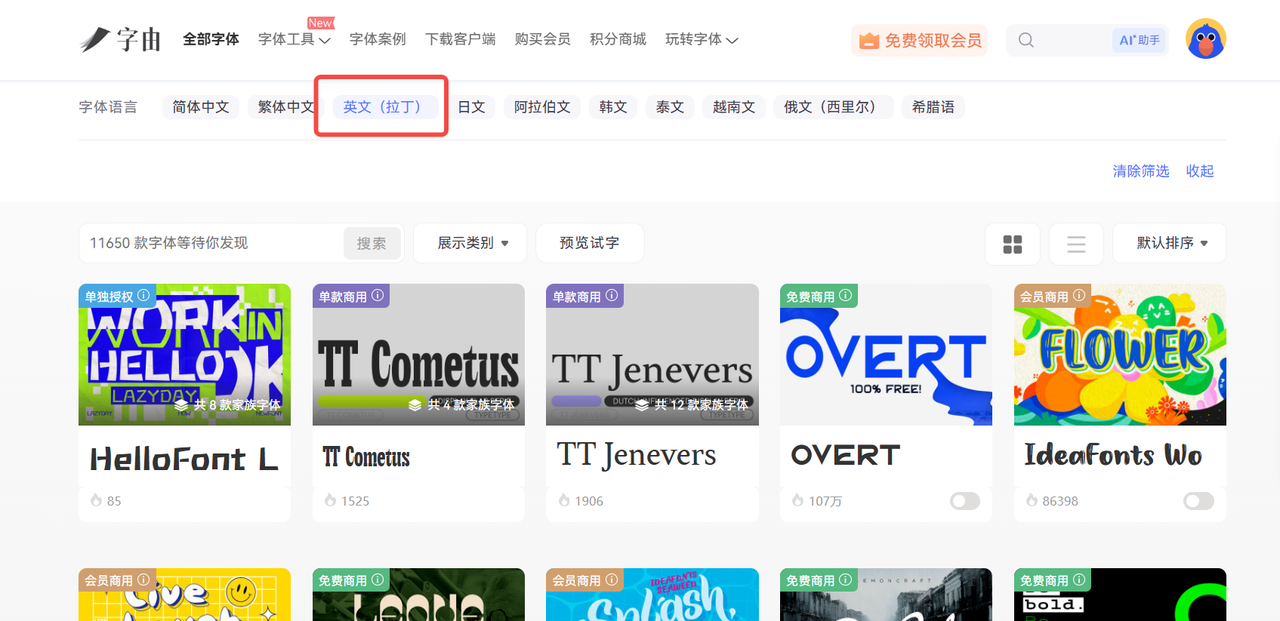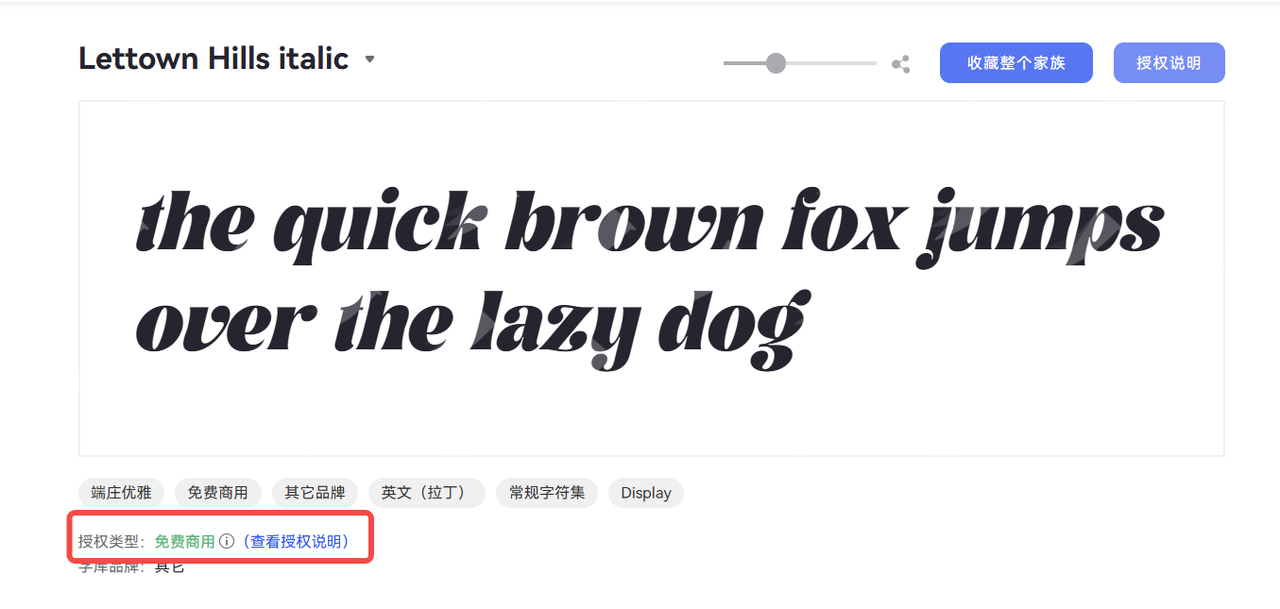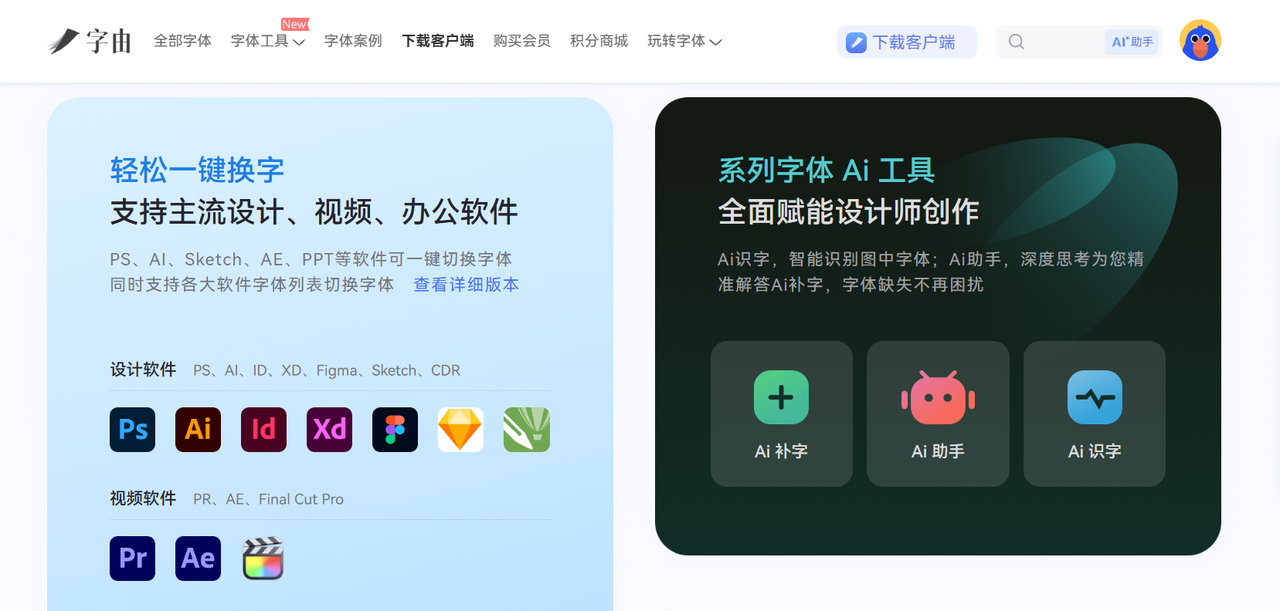
英文字体大全!6个值得收藏的英文字体网站推荐
在字体使用的过程中,很多朋友会发现,网络上提供的英文字体资源虽然数量较多,但找到符合设计需求并适合商业使用的字体并不容易。有些网站虽然字体数量丰富,但分类方式较复杂,需要花费较多时间筛选,反而降低了工作效率。今天本文就整理了 6 款备受专业设计师好评的英文字体网站,从国内到国外,从热门到小众,你想要的英文字体都可以尝试来这 6 个网站中寻找,一起来看吧!
1、字由:国产好用的英文字体网站,字体免下载
字由是一款国内常用的字体网站,但它不仅能提供中文字体,也能为你提供丰富的英文字体。我们在访问字由官网后,可以在站内直接使用关键词 “英文” 来搜索字体,或者将 “字体语言” 的条件设置为 “英文”,就能看到字由站内所有的英文字体了。
从热门到小众,字由能为你提供不同风格,不同类型的英文字体,满足你多种设计场景中的用字需求。
2、Fontspring
Fontspring 是一个专注商业用字的网站,相比一些以免费字体为主的平台,Fontspring 更加关注字体版权信息展示,适合需要用于品牌设计或商业项目的用户。
打开 Fontspring 官网后,我们可以按照字体风格、用途和设计类型来筛选站内的英文字体。比如标志设计、出版物设计、广告设计等需求,都能够找到对应的字体资源。
对于专业设计师来说,Fontspring 的优势在于他的字体信息展示比较完整。我们可以查看字体样式、支持语言以及授权说明,在选择字体前了解更多细节。
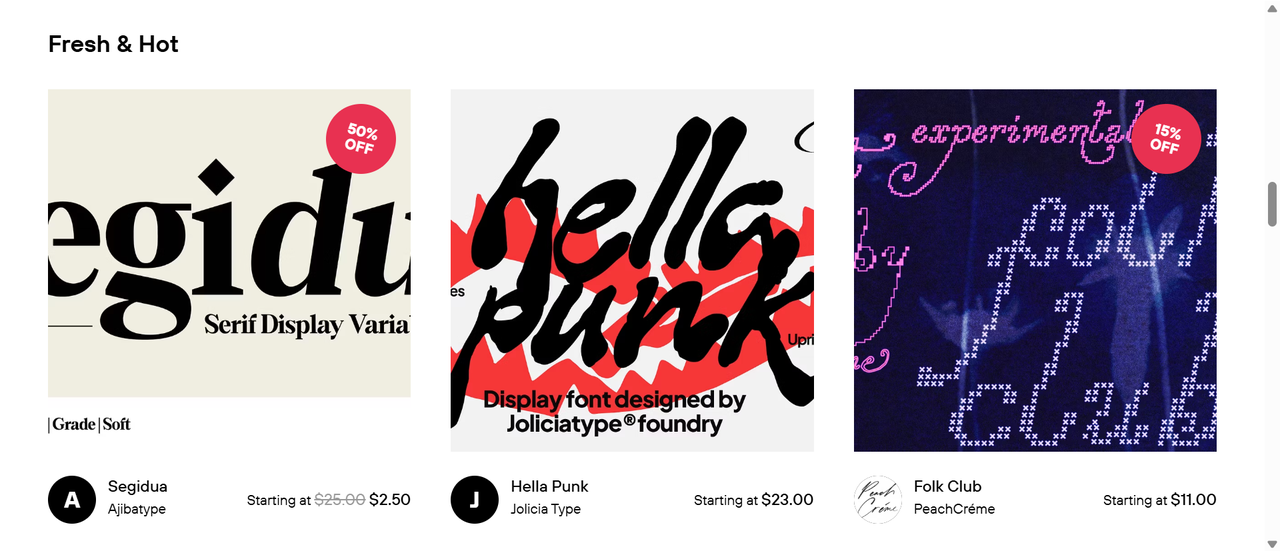
3、Fontfabric
Fontfabric 主要提供现代风格的英文字体资源,网站中主要提供简约字体、几何字体以及适合品牌视觉设计的字体类型。站内的部分字体支持免费使用,但同时也有商业字体,下载前我们要仔细查看字体授权,可以更好地确认字体是否满足使用需求。
Fontfabric 的字体展示方式比较直观,我们可以通过字体预览快速了解字体效果。对于需要制作 Logo、宣传页面或者商业海报的设计师来说,这种展示方式能够帮助判断字体是否符合整体设计方向。
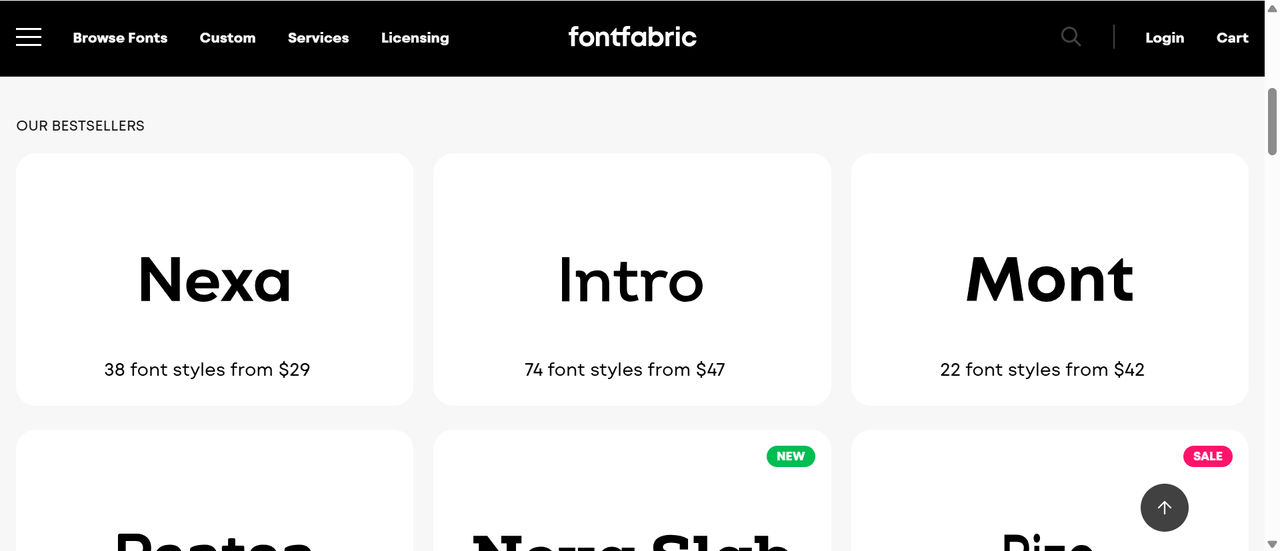
4、Lost Type
Lost Type 收录了许多具有创意感的英文字体,相比常见的英文字体网站,它更适合寻找具有个性表达的英文字体。
在进行设计时,如果普通字体难以体现作品特色,可以尝试从 Lost Type 寻找灵感,比如复古海报、文化活动宣传、创意品牌视觉等工作,都可以使用风格明显的字体增强设计表现。
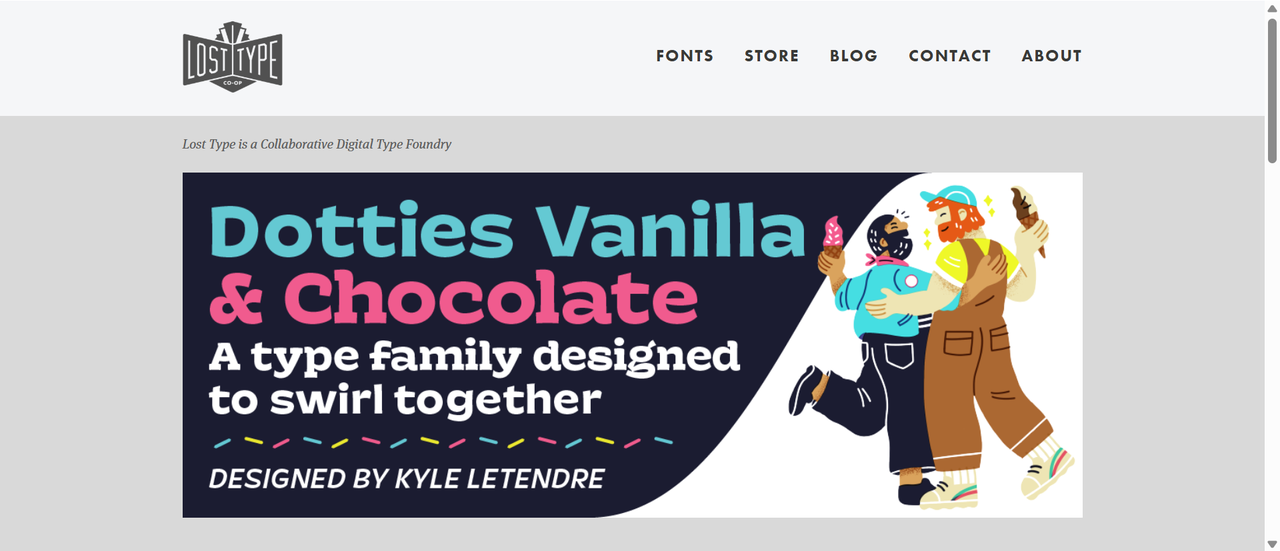
5、FontSpace
FontSpace 提供了大量的英文字体,我们可以直接根据需求来查找合适的英文字体。同时,FontSpace 也提供了方便的字体预览功能,我们可以直接输入自己的文案来查看实际效果,免去了要先将字体下载的麻烦。需要注意的是,站内不同字体的授权方式可能有所区别,因此在用于商业设计前,建议查看字体具体的授权说明。
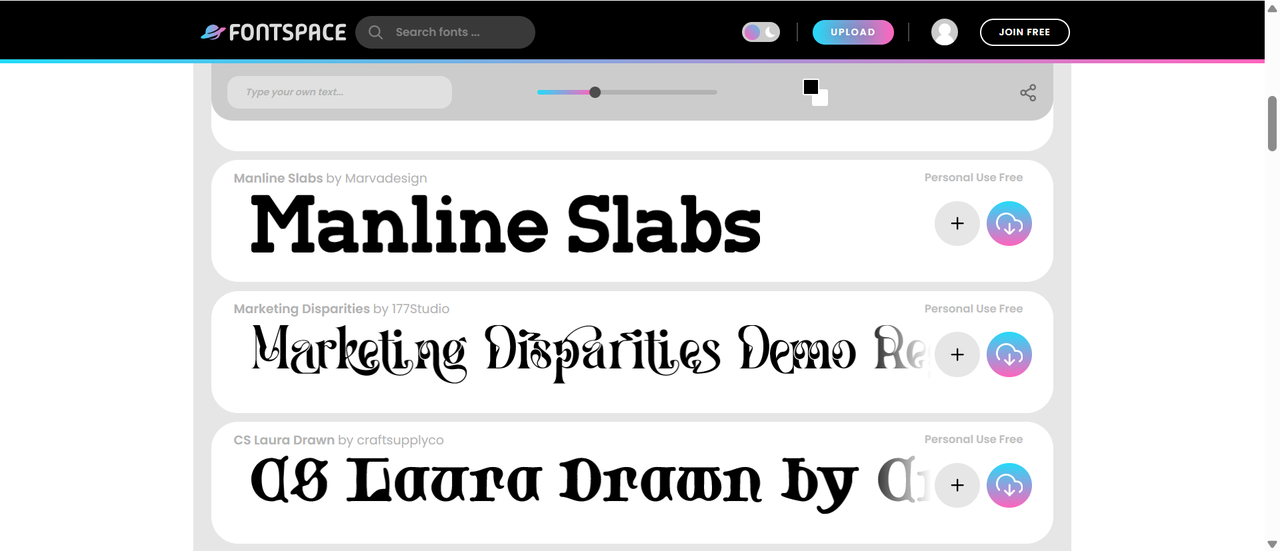
6、UrbanFonts
UrbanFonts 站内的字体分类覆盖手写字体、装饰字体、现代字体等多个方向,对于需要寻找特殊风格字体的设计师来说,UrbanFonts 也是个不错的选择。
在查找字体时,UrbanFonts 的搜索和分类功能可以快速帮助我们查找到不同的字体类型。比如我们要制作节日海报、活动宣传页面或者创意作品时,可以通过分类寻找符合主题的字体。